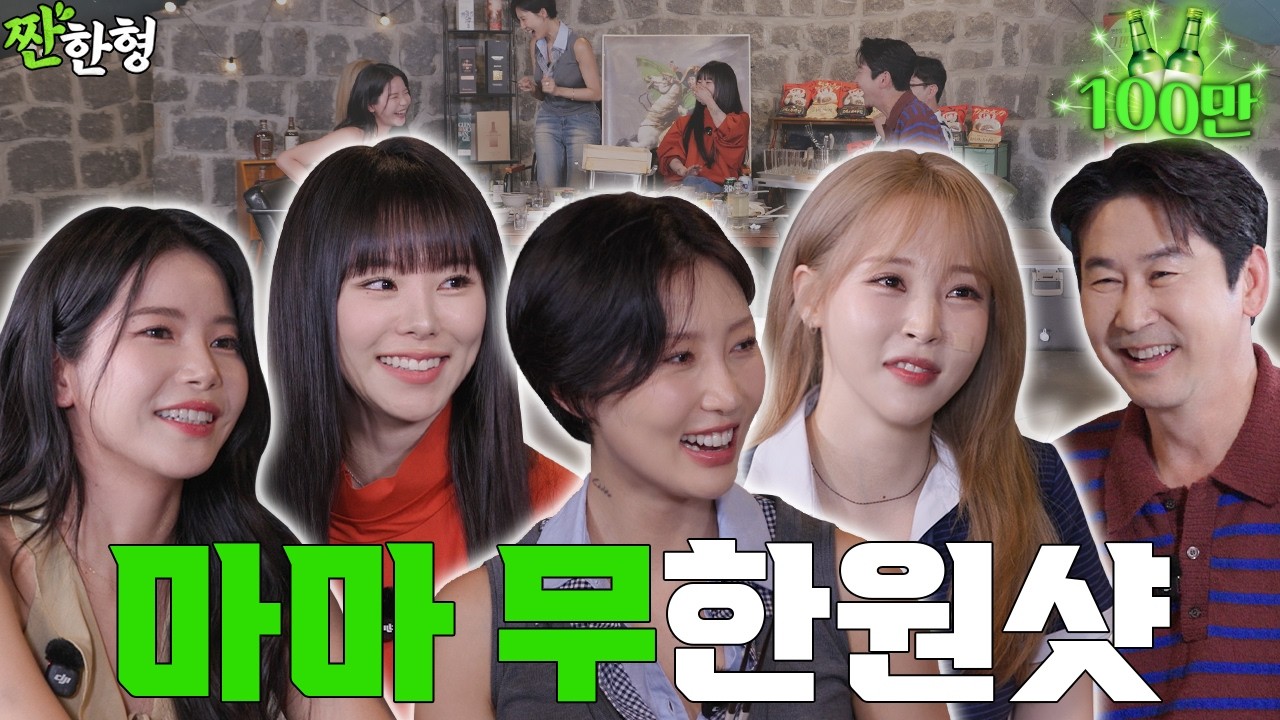
비트로코어 — (주)학산에서 배포하는 무료 폰트입니다. 두꺼운 획과 뚜렷한 삐침을 결합해 강한 인상을 만드는 장식 고딕체
부산의 스포츠 브랜드 비트로를 운영하는 학산이 2020년 한글날에 프라이드체와 함께 무료로 푼 서체입니다.
주목성이 필요한 타이틀에 어울리는 강하고 파워풀한 폰트라는 것이 배포 당시의 소개였습니다. 파일에서 재어 보면 자면을 채우는 비율이 매우 높아 굵고 진하며, 낱자가 가로로 퍼져 있어 짧은 문구를 크게 세울 때 힘을 냅니다.